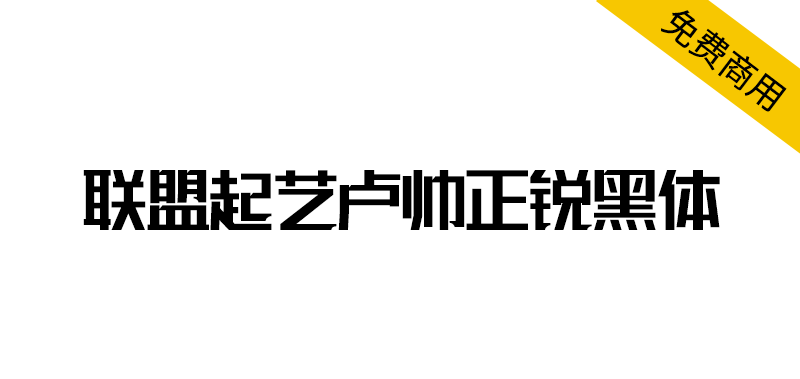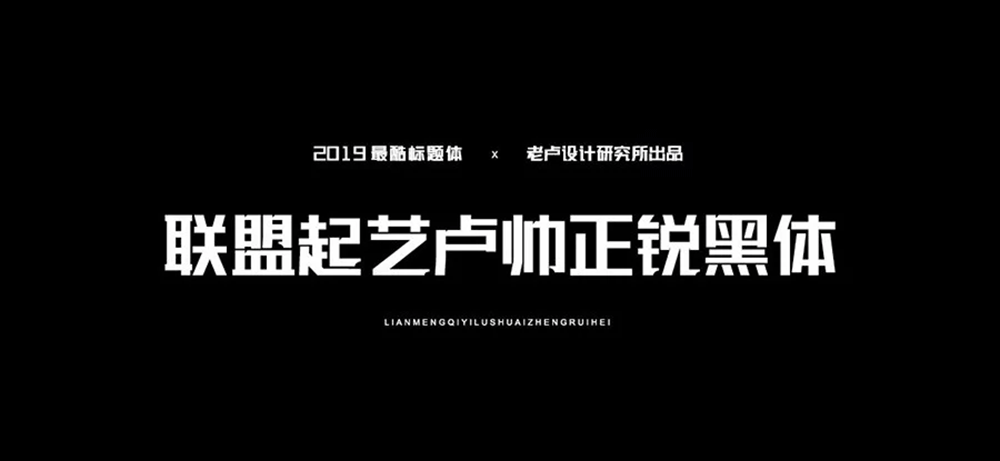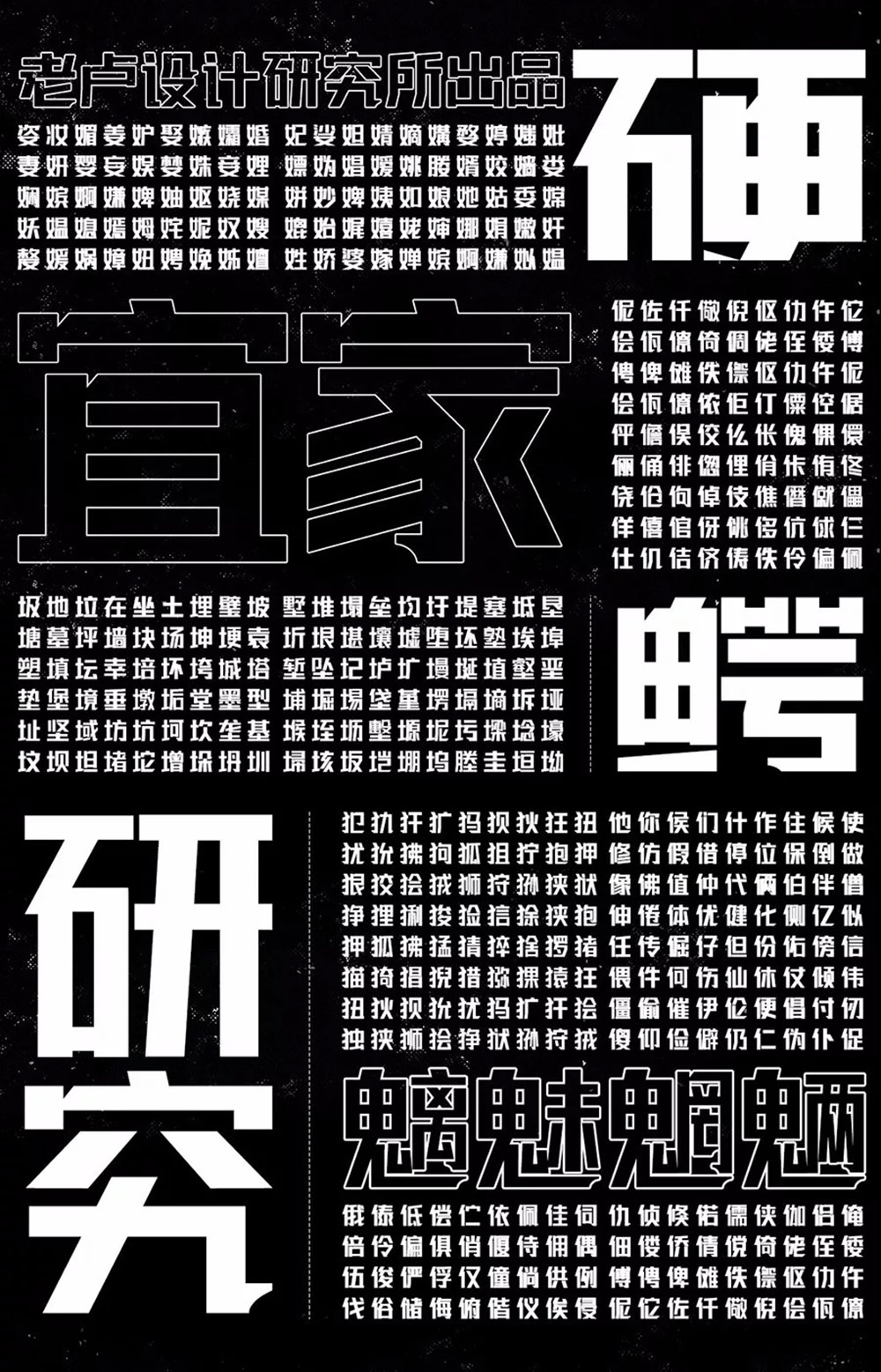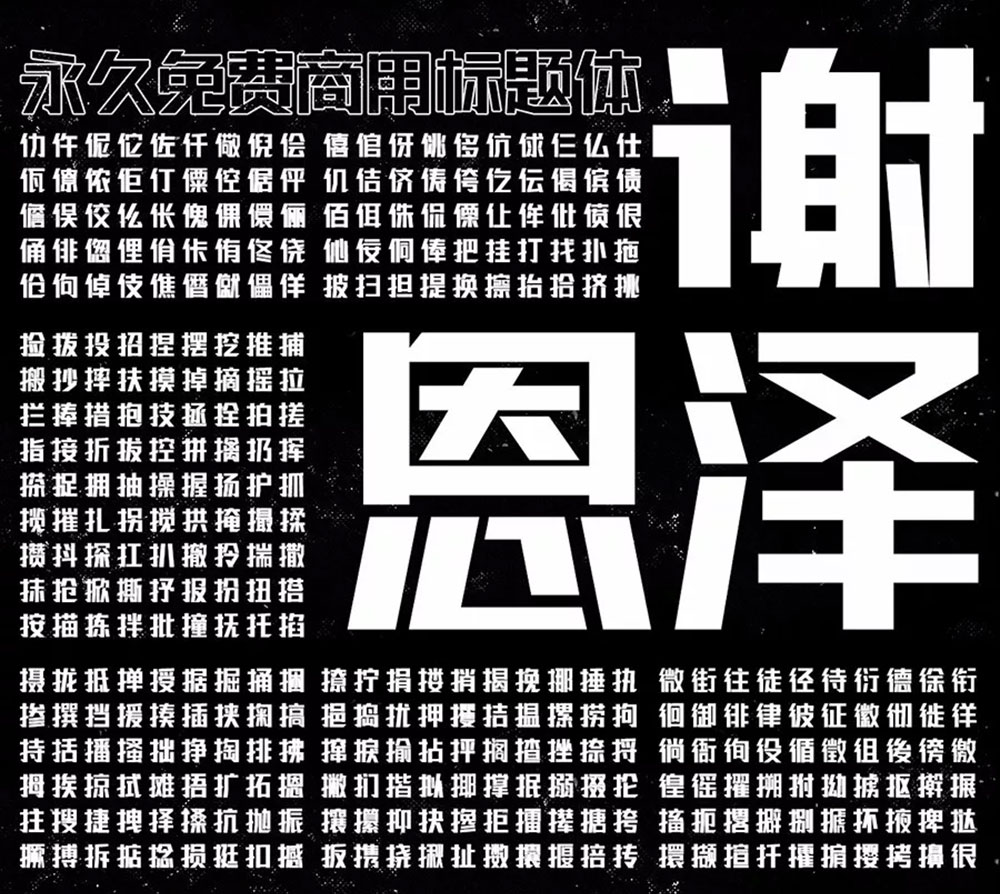
联盟起义卢帅正锐黑体共计8000余字,永久免费商用标题体!字库团队骨干设计师:凌旬(徐文博)、子轩、璐过炒米(李璐)、尚伟、小呆瓜(黄鑫)、狮子(郭培晟)、吕少惠
一款免费字体并不能改变世界什么,但希望我们的努力,能让“初心”重新回归到我们自己心中正确的位置。我们希望带给刚步入设计行业为字体版权头痛的你,正在设计行业沉沦为字体版权踟蹰的你,喜欢美好热爱生活的你,带来一次小小的感动。